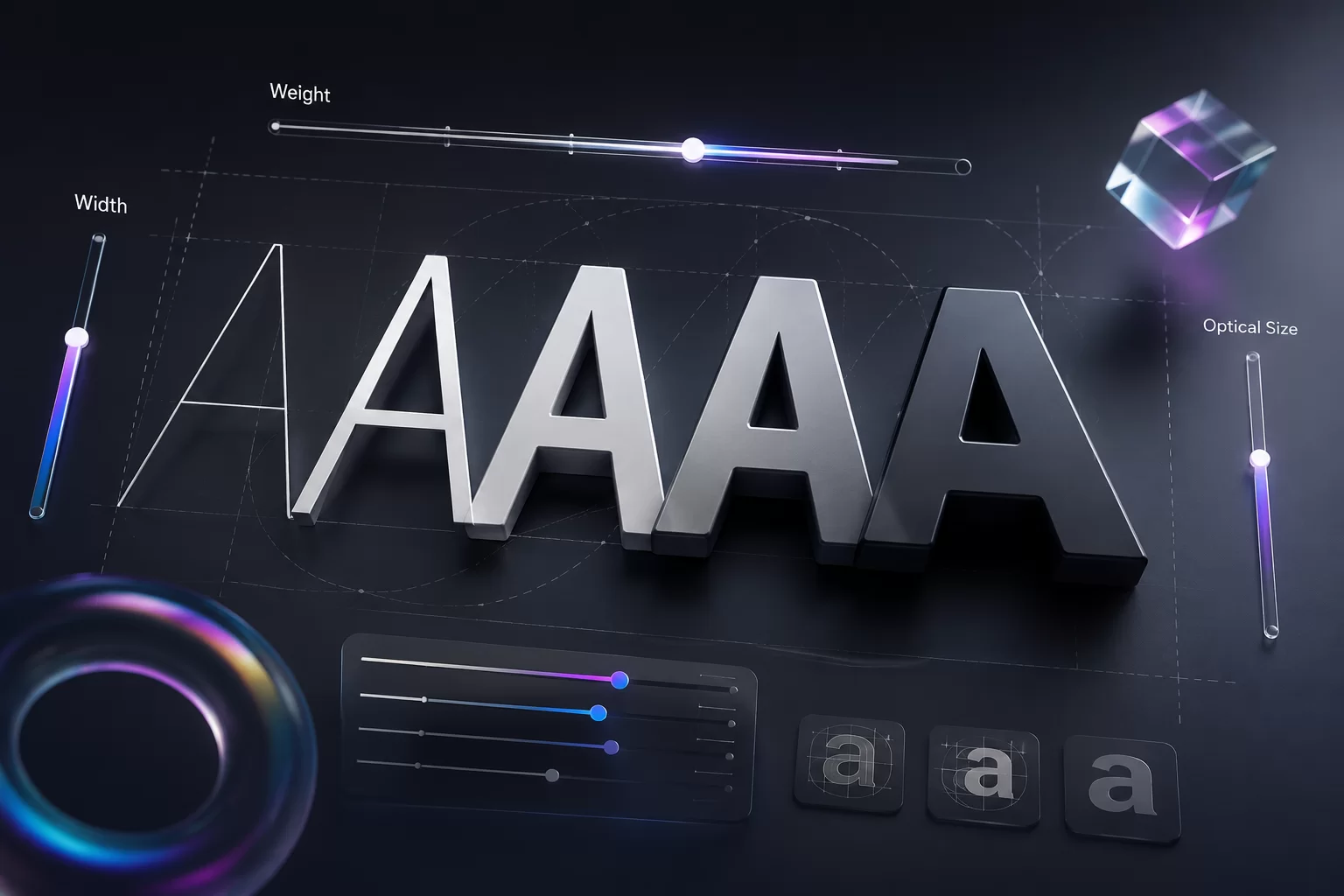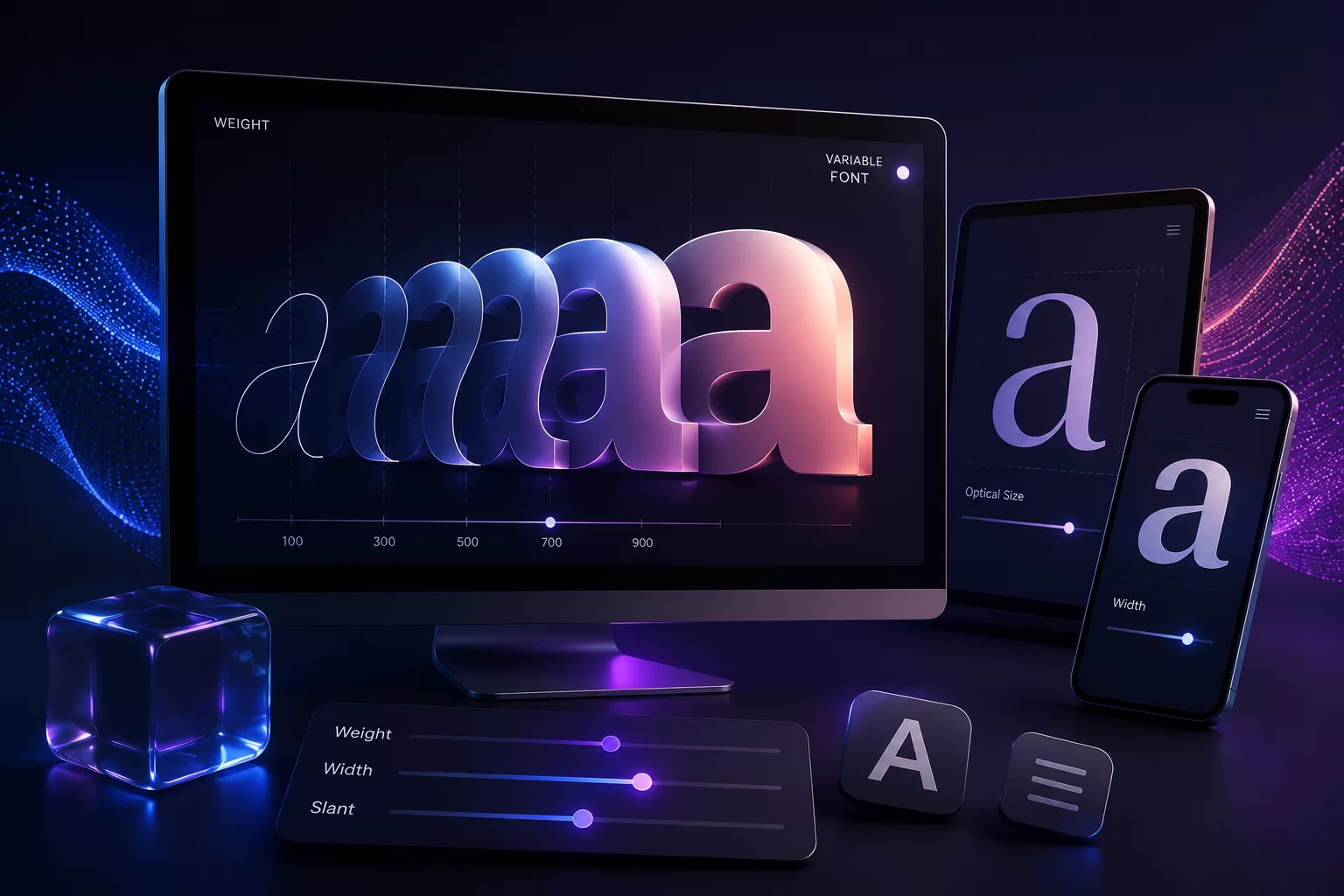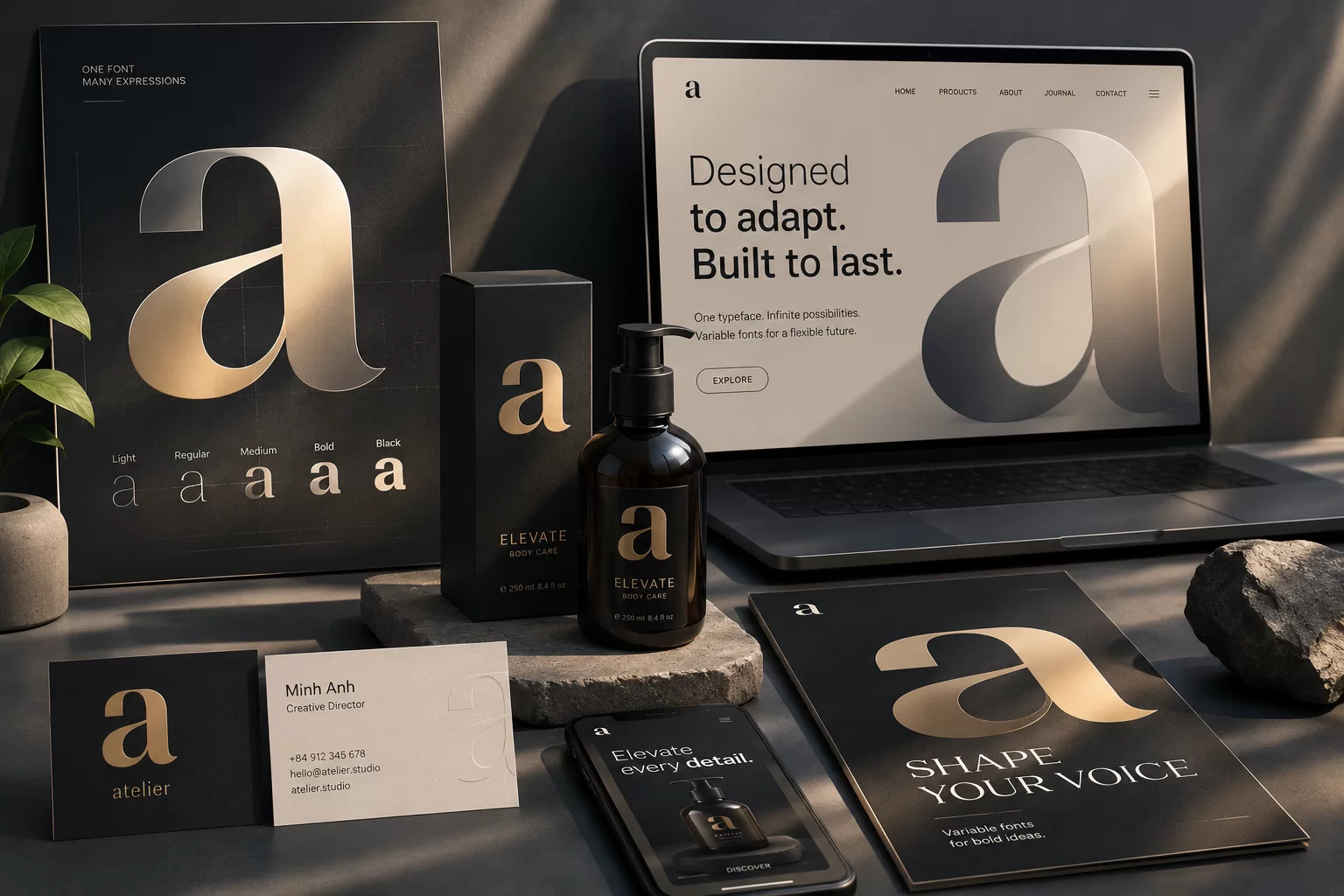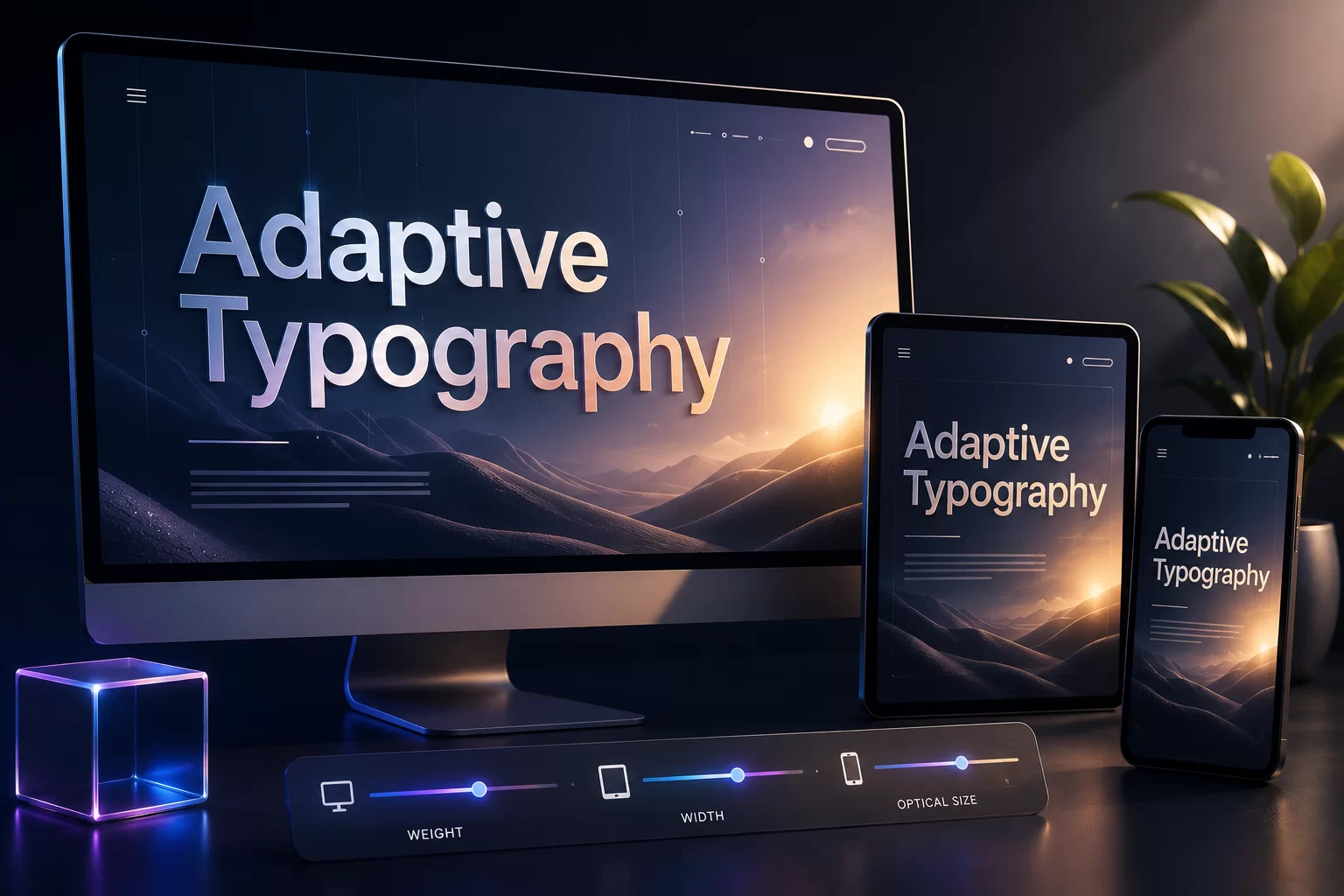
Typography chưa bao giờ chỉ đơn giản là lựa chọn một font chữ đẹp. Trong những năm gần đây, khi trải nghiệm số ngày càng được chú trọng, các nhà thiết kế bắt đầu quan tâm nhiều hơn đến khả năng thích ứng của font chữ trên nhiều kích thước màn hình, nhiều thiết bị và nhiều tình huống hiển thị khác nhau. Chính trong bối cảnh đó, Variable Fonts đã xuất hiện như một bước tiến lớn, mở ra cách tiếp cận hoàn toàn mới trong thiết kế typography.
Thay vì phải cài đặt hàng chục file font cho từng độ đậm, độ rộng hay kiểu chữ khác nhau, Variable Fonts cho phép tất cả những biến thể đó được gói gọn trong một file duy nhất. Điều này không chỉ giúp tối ưu hiệu suất mà còn mang đến sự tự do sáng tạo chưa từng có cho designer.
Nếu trước đây typography chỉ là một thành phần trong thiết kế thì ngày nay, Variable Fonts đang dần trở thành một công cụ sáng tạo mạnh mẽ, giúp chữ có thể thay đổi linh hoạt theo ngữ cảnh, thiết bị và trải nghiệm người dùng.
Variable Fonts là định dạng font hiện đại cho phép một file font duy nhất chứa nhiều biến thể khác nhau. Người thiết kế không còn bị giới hạn giữa những lựa chọn như Regular, Medium, Bold hay Black, mà có thể điều chỉnh trọng lượng chữ một cách liên tục theo từng giá trị.
Không chỉ Weight, Variable Fonts còn có thể thay đổi nhiều thông số khác như:
Ví dụ, thay vì chuyển từ Font Regular sang Bold, bạn hoàn toàn có thể chọn Weight 437 hoặc 682 để đạt được đúng cảm giác thị giác mình mong muốn. Đây là điều mà font truyền thống gần như không thể thực hiện.
Trong nhiều năm, website và ứng dụng thường phải tải rất nhiều file font khác nhau. Một bộ font hoàn chỉnh có thể bao gồm Regular, Medium, SemiBold, Bold, ExtraBold, Black cùng các phiên bản Italic tương ứng. Chỉ riêng typography cũng đã khiến dung lượng website tăng lên đáng kể.
Variable Fonts giải quyết gần như toàn bộ vấn đề này.
Một file font duy nhất có thể thay thế hàng chục file trước đây, giúp giảm số lượng request tải xuống, tối ưu tốc độ hiển thị và cải thiện trải nghiệm trên cả desktop lẫn thiết bị di động.
Tuy nhiên, điều khiến Variable Fonts thực sự nổi bật không chỉ nằm ở hiệu năng. Khả năng tinh chỉnh typography theo từng pixel giúp designer có thể tạo nên những bố cục cân bằng hơn, đẹp hơn và phù hợp hơn với từng nội dung. Đây là yếu tố mà những người làm branding, editorial hay website hiện đại đặc biệt yêu thích.
Một trong những thay đổi lớn nhất mà Variable Fonts mang lại là khái niệm typography động. Ngày nay, chữ không còn cần giữ nguyên hình dạng từ đầu đến cuối. Khi người dùng thay đổi kích thước trình duyệt, typography có thể tự điều chỉnh độ rộng để vẫn đảm bảo số ký tự trên mỗi dòng hợp lý. Khi màn hình nhỏ hơn, font có thể tự tăng Optical Size để dễ đọc hơn.
Trong các website hiện đại, tiêu đề còn có thể thay đổi Weight khi người dùng cuộn trang, hover hoặc tương tác với giao diện. Những hiệu ứng này diễn ra rất mượt mà vì tất cả đều được nội suy trực tiếp từ Variable Font thay vì chuyển đổi giữa nhiều file font khác nhau.
Typography từ đó trở thành một phần của trải nghiệm chứ không đơn thuần chỉ là nội dung.
Website hiện đại phải hiển thị trên rất nhiều kích thước màn hình khác nhau. Một tiêu đề đẹp trên màn hình 32 inch chưa chắc đã phù hợp với điện thoại 6 inch.
Variable Fonts giúp giải quyết bài toán này bằng khả năng Responsive Typography.
Designer có thể để font tự thay đổi Weight hoặc Width theo kích thước màn hình, giúp bố cục luôn cân đối mà không cần tạo nhiều phiên bản riêng biệt. Không chỉ đẹp hơn, cách làm này còn giúp giao diện trở nên thống nhất và chuyên nghiệp hơn rất nhiều.
Đó cũng là lý do ngày càng nhiều website lớn bắt đầu chuyển sang sử dụng Variable Fonts như một tiêu chuẩn mới.
Trong thiết kế nhận diện thương hiệu, typography luôn đóng vai trò rất quan trọng.
Một thương hiệu hiện đại thường xuất hiện trên hàng chục nền tảng khác nhau, từ billboard, poster, bao bì cho đến website, ứng dụng hay smartwatch. Variable Fonts cho phép cùng một bộ nhận diện có thể thích ứng với mọi môi trường mà vẫn giữ được bản sắc thị giác. Logo có thể dùng Weight đậm hơn.
Website sử dụng Weight nhẹ hơn để tối ưu khả năng đọc. Poster có thể mở rộng Width nhằm tạo cảm giác mạnh mẽ. Tất cả vẫn dựa trên cùng một hệ thống font thống nhất.
Đây chính là lý do nhiều thương hiệu lớn bắt đầu xây dựng cả hệ thống nhận diện xoay quanh Variable Fonts thay vì font truyền thống.
Variable Fonts mang đến rất nhiều tự do, nhưng điều đó cũng khiến không ít designer mắc phải những lỗi phổ biến.
Đầu tiên là lạm dụng quá nhiều biến thể Weight khiến hệ thống typography mất đi tính nhất quán. Việc có hàng trăm mức độ đậm không đồng nghĩa bạn nên sử dụng tất cả.
Sai lầm thứ hai là tạo hiệu ứng chuyển động quá mạnh giữa các giá trị font. Typography nên hỗ trợ trải nghiệm thay vì khiến người xem bị phân tán.
Cuối cùng là bỏ qua khả năng đọc. Một số designer cố gắng tạo những Weight quá mỏng hoặc Width quá hẹp chỉ để tạo cảm giác khác biệt, nhưng điều này lại khiến nội dung trở nên khó tiếp cận hơn.
Đối với thiết kế đồ họa, Variable Fonts mở ra nhiều cơ hội sáng tạo trong branding, poster và editorial. Đối với website, đây là giải pháp giúp cân bằng giữa tính thẩm mỹ, hiệu năng và khả năng hiển thị trên mọi thiết bị.
Trong bối cảnh trải nghiệm số ngày càng được chú trọng, Variable Fonts nhiều khả năng sẽ trở thành tiêu chuẩn mới của typography hiện đại. Hiểu và làm chủ công nghệ này không chỉ giúp designer tạo ra những sản phẩm đẹp hơn mà còn mang đến những trải nghiệm đọc tự nhiên, linh hoạt và phù hợp với xu hướng thiết kế trong nhiều năm tới.